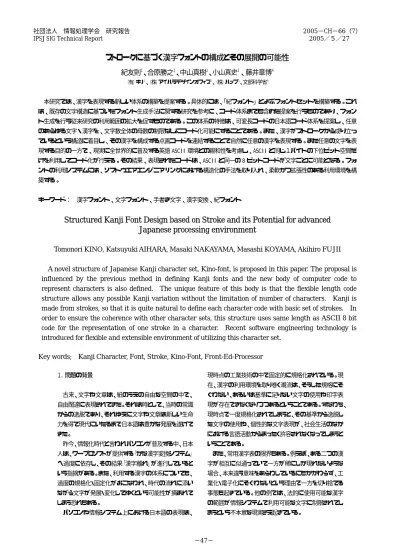
ストロークに基づく漢字フォントの構成とその展開の可能性
(2) 要するに、個々の文字の字形や字体は、工業製品とし. る。ホームページでは文字鏡文字の画像(24 ドット版と 96. ての既存の体系のうえで完全に商品化されている。この. ドット版)も無償公開し、使いたい文字画像の URL を書きこ. ため、現状ではパソコン上の文字に個人の筆跡の癖や特. むことで、利用者の WWW ページに文字鏡文字を表示する. 徴が入り込める余地はない。そこで、現在の文字生活の. ことができる。. 実態にてらして、日本の漢字の取扱いを総合的に検討す る必要性が増している。. e 漢字は、1997 年 10 月にユニコードの CJK 漢字2 万字 余の 24 ドットフォント(日本欄)から始まり、京都大学が. 科学技術政策の観点からは、こうした状況を踏まえた検. 1981 年に康煕字典の親字に通し番号を付けた『康煕字典. 討がされている。例えば、平成17年2月の文化庁の文化. 文字集覧』準拠の四万九千字余、大漢和辞典の 5 万字余、. 審議会総会では、「今後取り組むべき課題について」と題. 世界最大の漢字字典『中華字海』8 万 7 千字余をフォント化. して、「情報化の進展」に合致する「総合的な漢字政策の構. している。漢字を特定するには、大漢和辞典ならm、康煕. 築」、「漢字を手書きすることの重要性」等を提言している。. 字典ならkの後に検字番号をつけ、ユニコードならuの後. こうした政策課題が浮かび上がる背景には、情報機器の. に 16 進数をつける。現在では、約96,000 字のフォントが収. 急速な普及に伴い、一般の文字生活の中で、手書きをす. 蔵されている。. る機会が極端に減ってきていることから「漢字を手で書くこ. GT 書体フォントは、1995 年から日本語の文字を電子化. と」を教育や産業の中にどのように位置づけるかについて、. するプロジェクトとして推進され、現在では、約 6 万 6 千文. 検討する必要が生じている点が挙げられよう. 字を収録したフォントセットとなった。GT 書体フォントは、. 一方、情報技術の発達は、文字の情報の利用環境に関. TRON コードにも利用されている。TRON コードは、. して可能性をもたらしているといえる。例えば、近年のマ. BTRON3 仕様に、150 万文字を扱う TRON多国語言語環境. ルチモーダルなコンピュータインターフェース周辺技術の. として追加されたもので、実際に10万文字を超える具体的. 進展により、ワープロを越えて漢字を取り扱う環境が広が. 割り当てを行っている。. っている。また、先進的なソフトウエア設計論、プラットフォ. これらの大規模なフォントセットにおいては、外字の利. ーム、環境支援システム等を活用できる基盤が生まれつ. 用を行わないため、多くの字種をコードに割り当て、フォン. つある。すなわち、より柔軟性が高い漢字利用環境を実現. トを作成する方針を採っている。この方針では、新たな文. できる可能性がある。. 字を追加する場合、書体を統一してフォントをデザインす. 本論文では、こうした着想に基づき、漢字を表現する新. る必要性がある。また、文字情報を流通させる場合、流通. しい体系の構築を模索するものである。具体的には、「紀. する側とされる側で同一のコードとフォントセットを所有し. フォント」とよぶフォントセットを構築することが具体的な目. ている必要性もあるため、フォントセットの規模に比例して. 的となるが、その設計思想にソフトウエアエンジニアリン. 文字情報を流通させるために事前に必要な情報が増加す. グにおける構造化の手法を取り入れる。. る問題がある。今昔文字鏡においては、URL によって文字 を指定しフォントを取得することも可能であるが、ネットワ. 2.先行研究と本研究の位置づけ. ークに接続していることを前提としているため、利用機会 が限定される可能性がある。. 2.1. 大規模フォントセット 2.2. 文字の構造化によるフォント生成手法. 大規模文字フォントセット作成の先行研究として、今昔 文字鏡[7]、e 漢字[8]、GT 書体フォント[9]が挙げられる。こ. 本論文では漢字を表現する体系として、ソフトウエアエ. れらの先行研究では、文字の多様性に対処するという問. ンジニアリングにおける構造化手法を採用する。文字構造. 題に対する解決方法として、使われているあらゆる文字. を利用したフォント生成の従来研究としては、文字のストロ. のコード化を行い、大規模なフォントセットを作成するとい. ーク形状を基本要素としたエレメントを用いた骨格ベクトル. うアプローチがとられている。. を利用した研究がある[10]。これらは、フォント開発におけ. 今昔文字鏡は、1986 年からはじまったプロジェクトで、. るデザインの統一性や開発コストに着目し、文字の骨格構. 漢字学、中国文学、国文学、仏教学、歴史学など、さまざま. 造をフォント設計に利用する提案を行っている。また、TeX. な分野の研究者の支援のもとに構築したフォントを公開し. から利用できるフォント生成システムに. ている。現在、約12万文字が収録され、一部の書体の. METAFONT[11][12]がある。METAFONT は文字が幾何学. TrueType フォントと簡易検索ソフトの無償配布を行ってい. 的な曲線により構成されているとし、曲線を数学的に制御. −48−. 2.
(3) するプログラミング言語として定義されている。そのため、. その文字画像を得ることが出来るため、認識システム構. 自由にフォントを生成し利用するためには、高度な専門的. 築の際に必要となるデータベース作成にも利用できると考. 知識が必要となり、TeX 程一般的に利用されてはいないと. えられる。. 言える。 これらの研究は、フォントを生成する際の骨格情報の利. 3.基本構想. 用方法、それを基にしたストロークの描画方法について多 くの知見を与えるものであり、有用な研究であると言える。. 紀フォントの基本構想は、以上のような日本語の情報処. 先行研究にする本研究の特徴は、文字のコードを漢字. 理の現状を踏まえ、日本語本来の豊かな表現力をパソコ. の構造に合致させて体系するというものである。従来の文. ン上でより自然な形で実現する。すなわち、「まったく新し. 字構造に基づいたフォント生成手法に関する研究を参考. い文字を含む任意のあらゆる日本語文字を、環境に依存. に、コード体系までも含めた提案を行うものであり、従来研. せず自由にパソコン上で入力・表示・処理可能にする」こと. 究の利用範囲の拡張と言える。. である。また、手書き文字の特徴である「書き手個人の癖 や特徴の表現」を目指し、ひいては日本語とパソコン環境. 2.3. 文字認識研究おける位置づけ. とのより自然な融和をめざした拡張性のある処理環境を 提供することを目指す。. 本論文は、文字構造を利用した文字形状表現手法とコ. この設計思想を支援する発明は、文献[16][17]に挙げた. ード体系を提案するものである。近年、コンピュータにより. 二つの特許出願「ASCII コード化日本語」と「合成漢字フォ. 文字認識研究の新しい展開として、古文書を対象とした古. ント」である。以下、それぞれの着想を述べる。. 文書翻刻支援システム開発プロジェクト[13]が挙げられる。. 「ASCII コード化日本語」では、日本語を構成する文字種. このプロジェクトは、手書き文字 OCR 技術などを発展的に. を、音節文字のかなと漢字に分離する。かなの文字要素. 応用して古文書の翻刻を支援する認識システムの構築を. を音素とし、漢字の文字要素は点画に分解する。こうして. 目指したものである。古文書を電子化しコンピュータでの. 分解された両文字要素を ASCII コードのアルファベットの. 扱いを可能にするためには、現代で使用されていない文. 大文字小文字に対応したカタカナコード、ひらがなコード、. 字のコード化や翻刻結果の流通などを視野に入れる必要. 漢字点画コード、漢字部首コード等に分解分類する日本語. がある。古文書のような文書の場合、現在一般的に利用さ. のコード体系を構築する。現在、コンピュータ上での日本. れている文字とは異なり、同一の文字にも多くの変形や「く. 語の処理は、かな漢字混じり文を2バイトのコードで処理. ずし」が存在する。特に、日本語固有の平仮名においては、. している。このことは、高度な日本語を処理する処理系を. 漢字からの異なる変形によって作られた変体仮名、二文. コンピュータによって構成するためには制約となる。そこ. 字以上の仮名を一文字で表した合略仮名が存在し、現在. で、新しい日本語のコード体系を ASCII コード群と文字フォ. のコード体系では取り扱いが困難な文字がある。また、古. ントを関連付ける相互変換辞書を設けることによって、より. 文書の電子化の研究が進展するに伴い、新たなフォント. 柔軟で高度な日本語処理環境を実現することを目的として. 生成、コード化の必要性が生じてくると考えられ、そのよう. いる。. な要求に柔軟に対応できる技術が必要であると言える。古. また、「合成漢字フォント」とは、点画フォントを合成して. 文書翻刻支援システム開発プロジェクトの基盤となってい. フォントの体系を構成するものである。この基本となる点. る手書き文字 OCR 技術においては、現代の文字に対して. 画フォントは、ASCII コードに対応づけられた点画コード、. も、認識システム構築の際に利用する文字データベース. および補正値、座標軸の3要素で生成される。. の作成が大きな問題となっており、文字データの自動生成. 従来は、1文字1コードであったため、フォントセットはコ. 手法の提案なども行われている[14][15]。これらの研究に. ードに利用可能な情報空間の量に制約を受けた。特に、. おいては、人が書いた文字画像データや筆跡情報を元に. 日本語も外字などの特殊な文字の処理は、異機種間では. 新たな文字画像データベースの生成を行っている。その. 同一の表示ができないなどの問題を生んだ。そこで、必要. ため、新しい字種のデータ生成の要求があった際、その. 最小限の漢字フォントを所持し、必要に応じて漢字フォント. 字種のサンプル収集を行わなければならない。本プロジ. を増減できるようにするなどの課題を解決するために、漢. ェクトで提案する技術は、文字の形状のコード化を実現す. 字要素の点画フォントの組み合わせで漢字フォントを作る. るものであり、新たな字種のフォントやデータベースを作. ことを考案した。. 成する場合、文字の形状を表現するコードを生成すれば. −49−. 3.
(4) 4.「紀フォント」システムの設計. を割り当てる結果となるこのような体系は、非常に効率の 悪いものと考えられた。このため、こうした体系がその後. 紀フォントは、上述した設計思想のもとで具体的には、. のコンピュータ技術の進展のなかで発展する素地が得ら. 以下で説明する「紀(Kino)コード」と「紀(Kino)フォント」によ. れなかった。しかし、今日の演算速度の高速化、通信容量. って構成する。Kino コードと Kino フォントを実装した. の増大という環境においては、このようなコード体系が利. 「KinoFont」アプリケーションによって、フォントの利用者に. 用できる環境にあると考えられる。. 対して、Kino コードへの変換機能、独自のフォントを定義 する機能等を提供する。以下では、具体的にこれらの説明. 4.3 Kino フォント. を行う。 Kino フォントは、任意のあらゆる文字や漢字をできるだ 4.2 Kino コード. け制約なしに取り扱うことを目的としている。現在の汎用 OS では、日本語処理環境や特定のフォントセットを利用者. これは、任意のあらゆる文字・漢字を文字数全体の母. が選択する余地は少ない。そこで、こうした環境に依存せ. 数の制限なしにコード化可能にするために考案された可. ず、多様なヒューマンインターフェースを可能とする各種. 変長コードの日本語コード体系である。漢字の文字構造に. デバイス上に、自由に文字の可視化や印字を行うために. 即して、その漢字を構成する点画コードを連結することで. 考案した技術である。. 自然に任意の漢字を表現する。. Kino フォントは、あらかじめ具体的な印字形状(タイプフ. また任意の文字を表現する目的の一方で、現実に全世. ェース)データを用意せず、文字自身の幾何学的な論理構. 界的に普及する英語 ASCII 環境との親和性を考慮し、. 造だけに基づき文字を構成している。この着想は、本来文. ASCII と同じ1バイトの下位ビット空間だけを利用してコー. 字は、限られた基本的なストロークの組あわせによって成. ド化が行えるよう考慮されている。その結果、表現された. り立っているという事実に基づく。. コードは、ASCII と同一の 8 ビットコードが文字ごとの可変 長として連続するコード表現となる。 図1は、Kino コードの適用事例である。紀フォントでは、 漢字を構成するストローク=点画を一つの ASCII コードであ るアルファベットに対応させている。この例で、「鎌」は、1 8画からなる漢字であり、それぞれの点各に対応する18 文字のアルファベットからなる。例えば、「w」は、右むきの ハネをあらわすので、同様のストロークは、「倉」「知」「人」. 図2 Kino フォントにおける印字形状の定義. の第一項に現れている。 図2は、「七」という漢字が、二種類のストロークで成り立 ち、これらのストロークの大きさと位置関係を規定すること により文字を定義していることを表している。 4.4 Kino フォントの実装 図1 Kino コード適用事例 「KinoFont」アプリケーションは、内部にリスプインタープ 従来のように漢字体系を固定長のコードの各アルファベ. リタを内臓し、Lisp 言語の S 式コマンドの評価によって動. ットに対応付ける方式では、固定長サイズによって利用で. 作する。このため、フォントを規定する各種データの外部. きる漢字の数に制限が生まれる。Kino コード特徴は、まず. 表現も Lisp 文のフォーマットになっている。. 漢字を構成するストロークの種別がせいぜい英文字アル. また、利用者が容易に Kino フォントに触れられるように、. ファベットのオーダーと同等の記号で表現できる点に着目. Java で実装したユーザ利用環境をウェブで公開している。. している。欠点としては、画数の多い漢字はそれを表現す. 公開サイト http://www.kinofont.jp/ を是非参照されたい。. るアルファベット文字列が長くなることである。 コンピュータが発明された当初、文字に長いメモリ空間. −50−. 4.
(5) 4.5 ストロークを基礎とする漢字の構造化. 5.2 フォント生成手法からの観点. 今後の課題として、紀コードのより高度な利用環境を構. フォント生成手法の観点から、若干の考察を試みる。ス. 築することを目指して、コードのメタデータをセマンティック. トロークを基に、個別のフォントを生成するという着想は、. ウェブ技術の利用のもとで構造化することを検討している。. 既に80年代に文献[12]等によって処理環境として確立さ. 漢字を部首に基づいて分類し、そのメタデータに基づいて. れている。このため、この点だけの技術的に評価に留まる. 構造化する試みは、先行研究の文献[8]などで実施されて. と、紀フォントの新規性は乏しい。例えば、TeX の ME. いる。. TAFONT や従来のフォントのデザイン手法においても紀フ. 本研究では、点画ストロークに基づいてフォントを構成 する。そのため、①ストロークのレベル、②部首のレベル、. ォント以上の技術的提案はなされている。 ただし、コード体系を柔軟に構成しているという視点は、. ③漢字のレベル、④漢字体系に係るメタデータのレベル. 提案の独自性・新規性が主張できる点であると考える。コ. など一つの文字に関して、4層程度の階層構造を持たせ. ンピュータの処理系の根底には、8ビットによる ASCII コー. ることが考えられる。これによって、より柔軟な文字の運. ド体系が存在する。そこで、このASCIIコードを最低限の前. 用を例えば、セマンティックウェブ技術を用いて実現すると. 提とした上で、拡張性のある柔軟なコード体系を取りうると. いうことが考えられるため、現在検討中である。. いう観点は独自であり、今後の情報処理システムの進化 を展望すると有効性が期待できる。. 5.紀フォントの評価. 例えば、ウェブ技術においては、文書情報を構造化して 流通させるために、XML などの汎用的なデータ記述手法. 5.1 大規模フォントセットとしての評価. が発達している。また、知識処理は、セマンティックウェブ 技術の体系などを利用し、こうした構造化した情報の上に. 大規模なフォントセットを構成するという先行研究の代. 構築される。そこで、特殊な漢字や手書き文字・文書を構. 表は、文献[7][8][9]である。これらは、確固とした設計思想. 造のある情報として流通させるという観点からは、このよ. の上に拡張性のあるシステムが既に構築されており、. うな情報流通技術との関連性において本システムの優位. 種々のフォントをワープロ上で活用するという観点では、. 性が期待できる。. 完成の域にあるといえる。. 一方、本稿で充分な検討がなされていない点として、定. 本稿で提案した紀フォントが従来の設計と異なる点を明. 量的評価の不足が挙げられる。例えば、外字を多く含む同. 示すれば、「文字や文章は紙の上の自由な空間の中で自. 一の文書を幾つかの方式でコード化した場合のデータサ. 由闊達に表現されるべきである」という発想に基づくシス. イズなどの定量評価が必要であろう。その上で、紀フォン. テムの設計思想を持つ点である。むろん、我々のこれま. トの性能や適用範囲を他システムの場合と比較し、有効な. での研究成果では、この思想を充分反映しているとはい. 適用領域の範囲を明確するべきであろう。こうした評価は、. えない。しかし、従来方式が、今後の情報通信技術の進化. 今後の我々の研究における課題であると考える。. の方向を考えた場合に、一つの処理環境として有効利用 される可能性があり、検討の余地があろう。. 理想的な、METAFONT のようなある種プログラミング言 語的な表現手法を取り込める拡張性を有したシステムへ. 拡張したフォントを利用する場合は、文書のやり取りに. 発展出来れば非常に有用なものになると期待できる。. 際して、各自の処理システムに同等のフォントセットが必 要である。メモリ容量が増大した今日こうした環境を持つこ. 5.3 文字認識への応用可能性. とはさして負担ではないかもしれない。漢字に係る情報の 流通のモデルは、現状ではこうした環境で完結している。. 紀フォントはあくまで文字を表現するための体系である. しかし、ユビキタス化といわれる多様な情報入出力端末が. が、これを利用すると手書き文字の認識において、処理の. 普及すること、情報環境とロボットなどの融合領域におけ. 効率化、認識精度の向上に繋がる可能性が考えられる。. る技術進展が見込まれることなどを勘案すると、別の「手. 従来の 文字認識手法に つ い て は 、 例え ば 、 文献. 書き文字・文書」流通の発想が可能である。本提案は、文. [1][3][5][14][15]にあげたような文字の骨格情報を利用し. 書のコード化自身にその表現を生み出す構造を内包する。. たものが挙げられる。本稿での提案は、必ずしもこうした. この点は、本研究の特徴と考えられる。. 既存研究に対して何らかの新規性を主張するものではな いが、これらの文献に述べられている手法と親和性があ. 5 −51−.